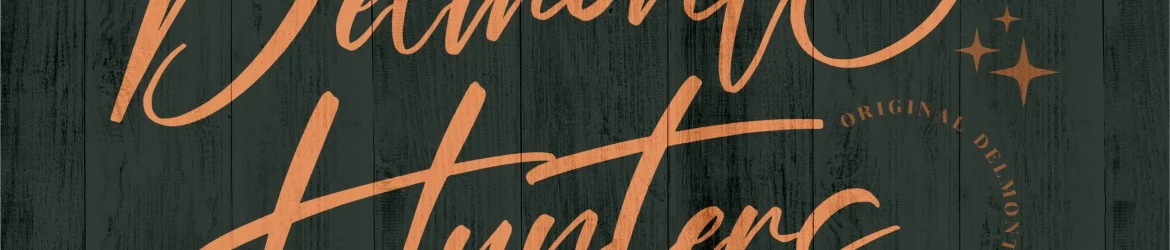
Delmonte Hunters Font – Download Grátis
Delmonte Hunters Font é uma elegante escolha para qualquer projeto que exija um toque personalizado e sofisticado. Inspirada nos traços naturais de uma pena, esta tipografia escrita a mão se destaca por sua versatilidade, adequada não apenas aos logos e projetos de marca, mas também a designs para itens de casa, embalagens de produtos, taças de tchê, cartazes, sacolas de supermercado, revistas e até mesmo materiais de convite. Seu charme único faz dele uma excelente opção para qualquer projeto que busque um toque premium, seja ele em um mala de tênis, etiquetas gourmet ou simplesmente em um papel de carta especial. Com Delmonte Hunters Font, você pode criar designs memoráveis e personalizados, tornando seu trabalho ainda mais único e sofisticado.